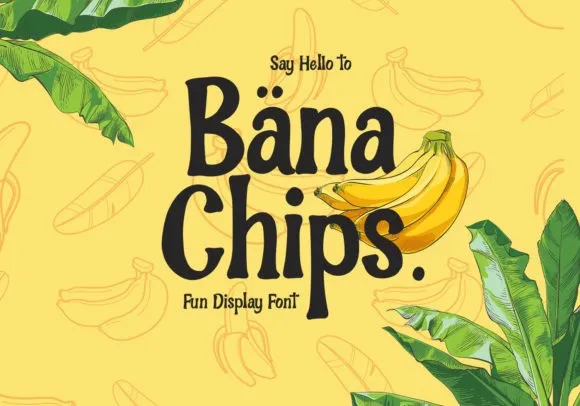
Descubra a encantadora Bana Chips Display Font, uma fonte cuidadosamente criada para designers que buscam uma combinação única entre elegância e autêntica escrita manual. Esta fonte é exatamente aquela que você vê em capas de livros best-seller e até mesmo nos cartazes de filmes, pois seu designer atento às nuances da escrita fez um trabalho meticuloso para capturar o encanto das letras manuscritas. Bana Chips apresenta uma elegância cuidadosamente equilibrada com a autenticidade do estilo tradicional. Com sua arquitetura clássica e seu toque fresco, esta fonte é perfeita tanto para projetos profissionais quanto para design de arte original. Suas linhas finas e robustas, combinadas com um brilho natural que parece ter sido trazido do papel, criam uma atmosfera única e enigmática. O Bana Chips é a escolha ideal para quem deseja destacar-se em seu trabalho através de designs inovadores e impressionantes. Ele combina o encanto dos tempos modernos com os segredos da arte manual, criando um equilíbrio único que ressoa com uma geração atenta ao passado enquanto olha para o futuro. Escolha a Bana Chips para suas próximas criações e deixe seu trabalho soar elegante, autêntico e originalmente inspirador.